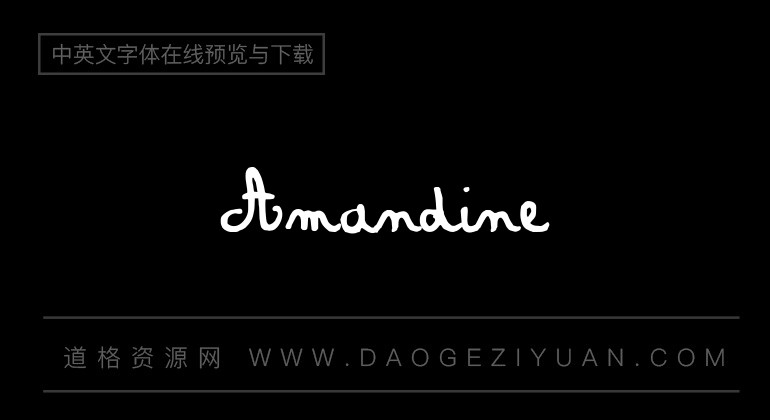
Amandine 是一款由日本设计师Kazuhiro Yamada设计的字体,它是一款现代感十足的英文字体,属于西文字体。它具有简约而不失活力的线条,拥有优雅而稳重的气质,可以用于各种不同的场景,比如商业广告、书籍封面、海报等等。Amandine字体具有良好的可读性,拥有清晰可见的字符,可以让你的文字更加突出。内容介绍
Amandine是一款非常不错的手写艺术字体,具有很好的视觉感,适合于文化类的宣传设计、商业类品牌的广告和产品包装设计以及个性化文字排版等较多场景。